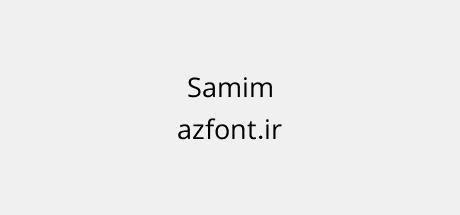
Samim
فونت زیبای رایگان Samim
قلم زیبای Samim از سری قلم های بسیار زیبا برای تایپوگرافی و لوگو تایپ می باشد.این قلم در وزن Regular و توسط
DejaVu fonts team - Redesigned by Saber Rastikerdar